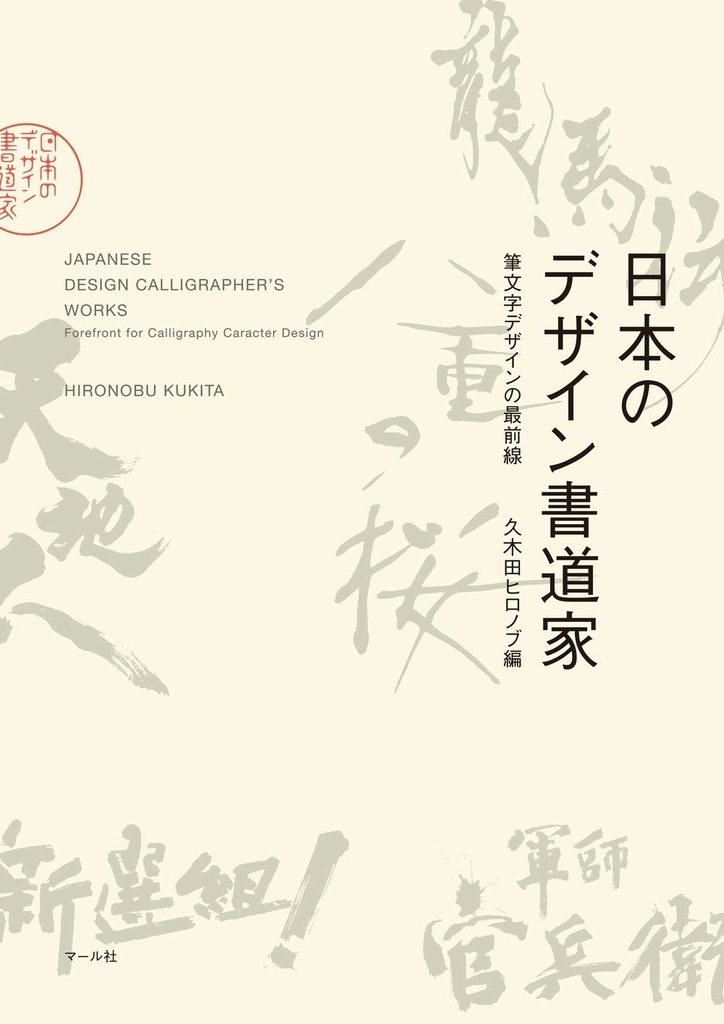
日本のデザイン書道家
29年にわたりデザイン書道作家として、テレビCMやポスター・書籍等の広告筆文字作品も手掛け、またデザイン書道の講師として指導に携わり、日本各地でワークショップを展開し多くのデザイン書道作家を輩出している久木田ヒロノブ氏編集による「日本のデザイン書道家」がマール社から2018年12月21日に発売された。
「日本のデザイン書道家」では第一線で活躍する書家や筆文字クリエイターの作品を作家ごとに掲載。更にデザインの考え方や制作の秘訣も紹介している。
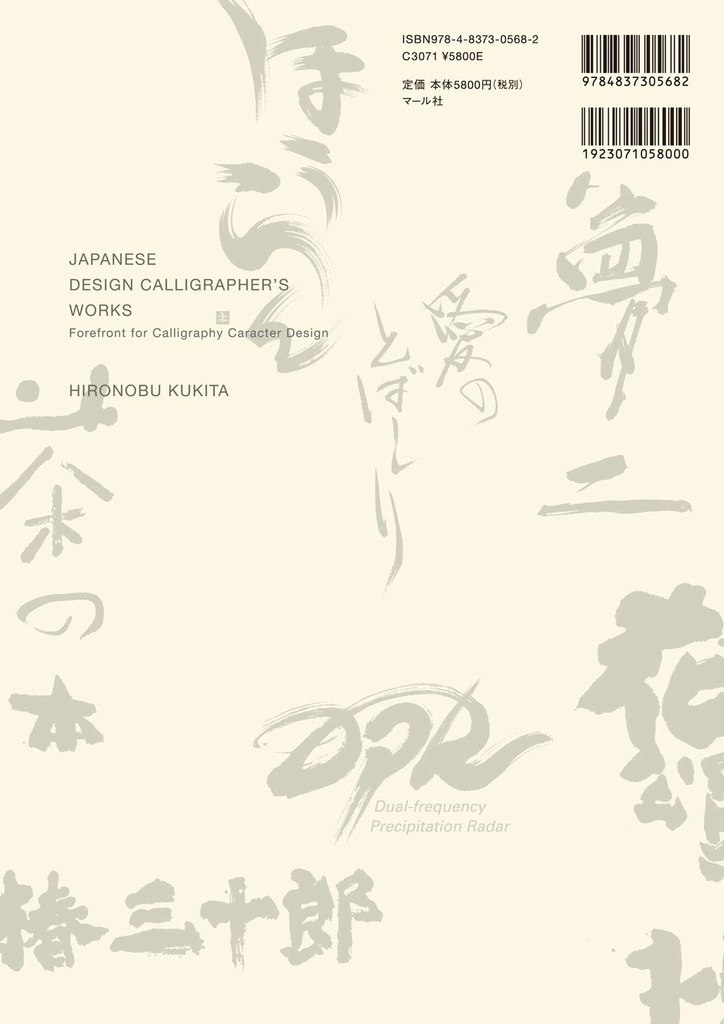
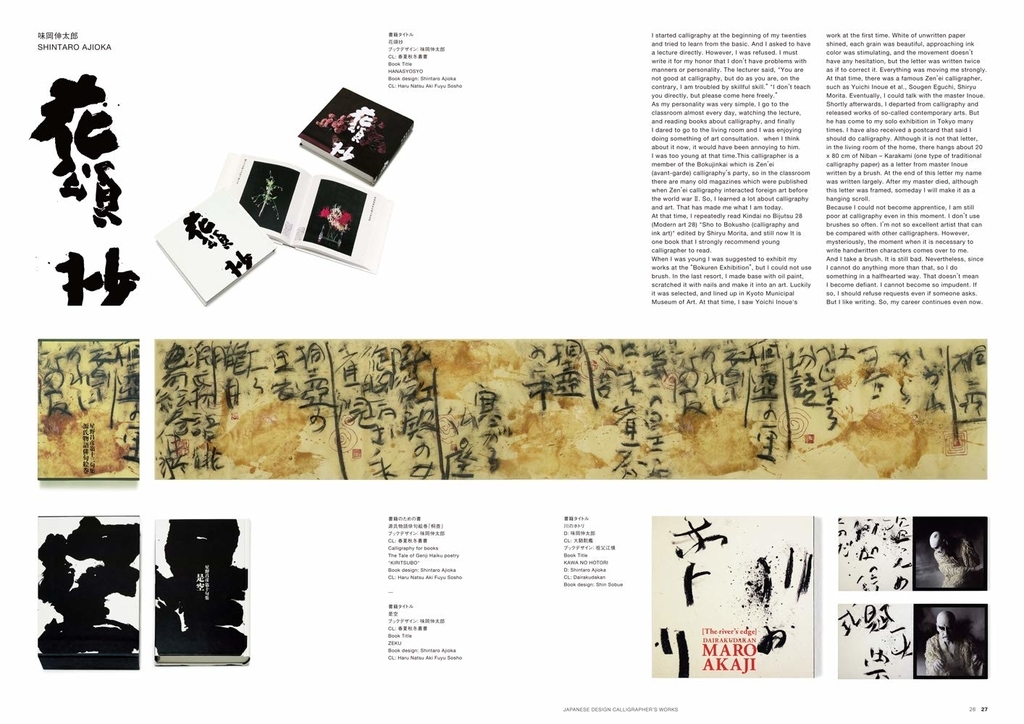
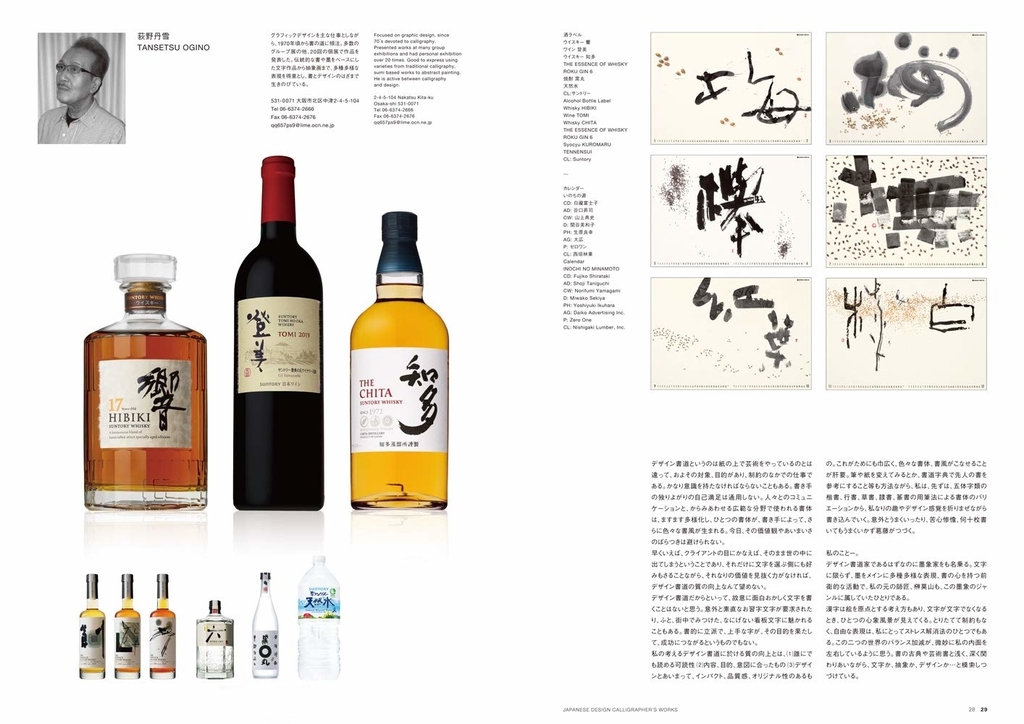
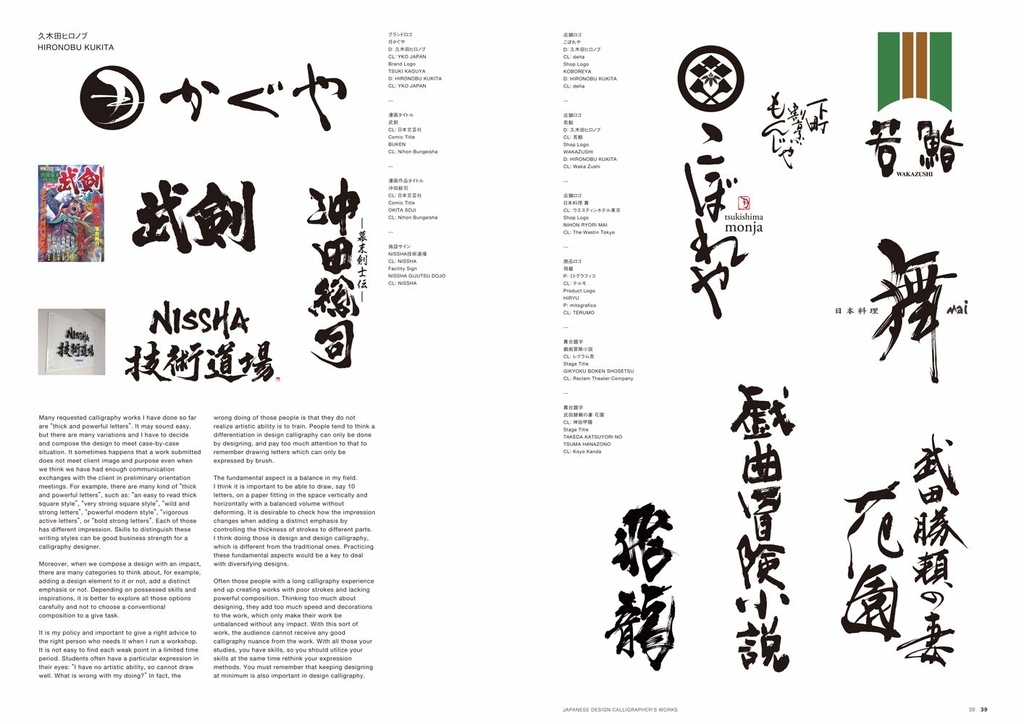
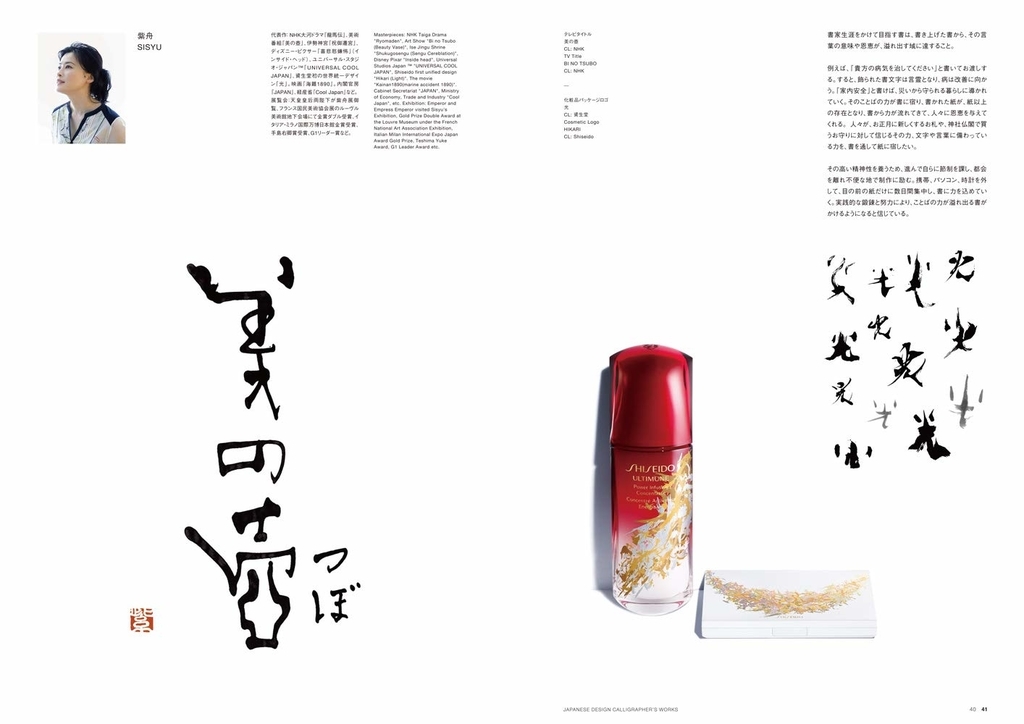
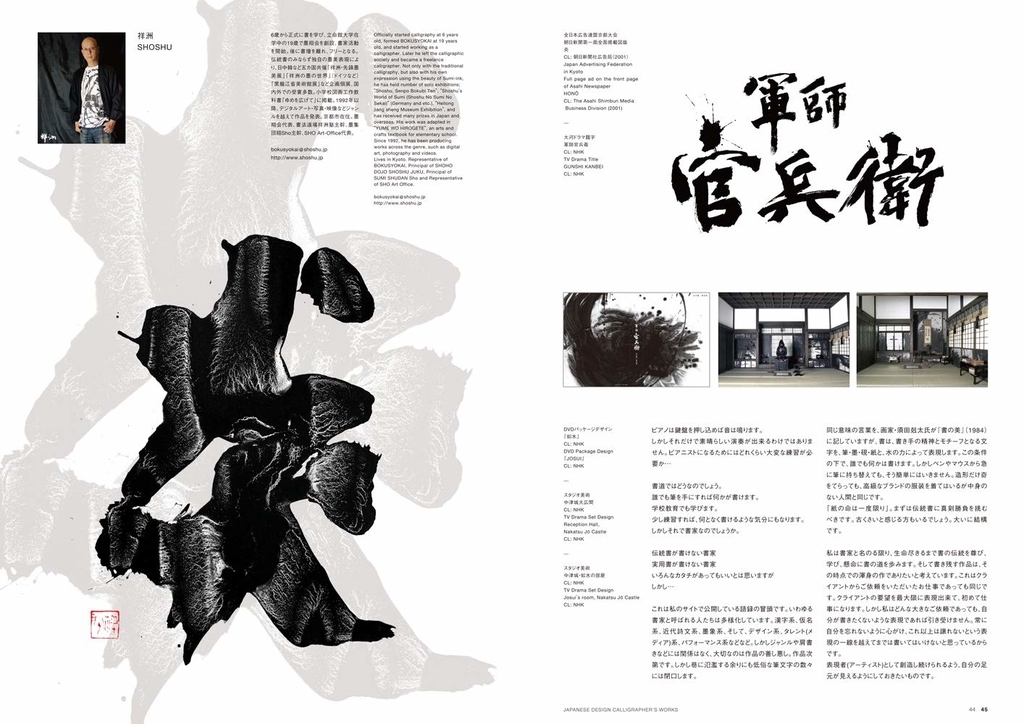
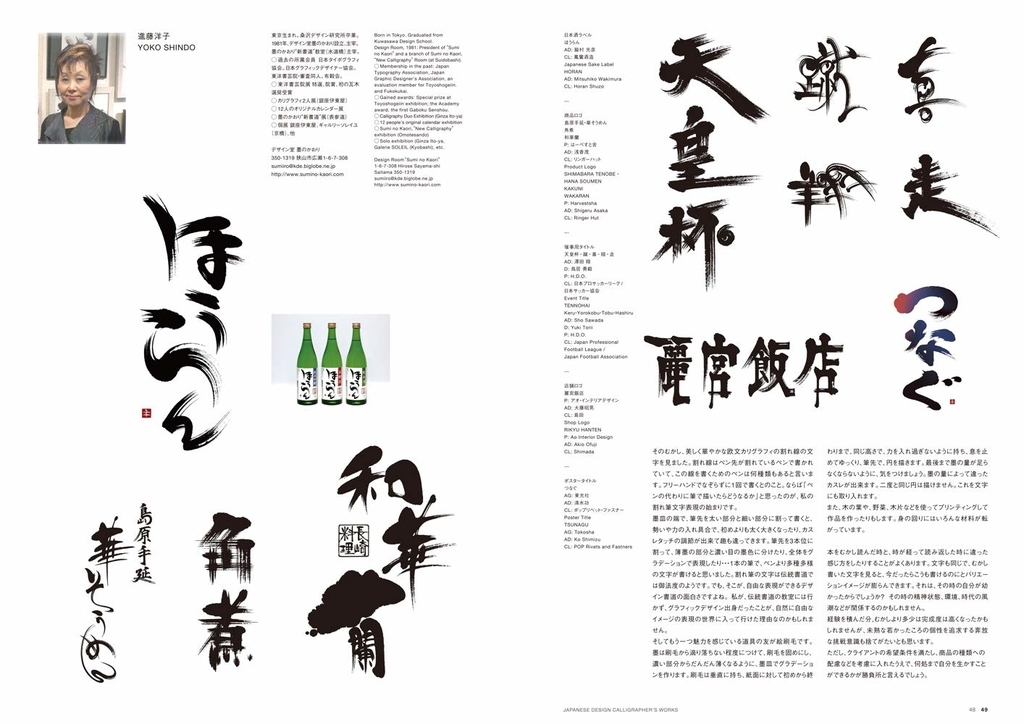
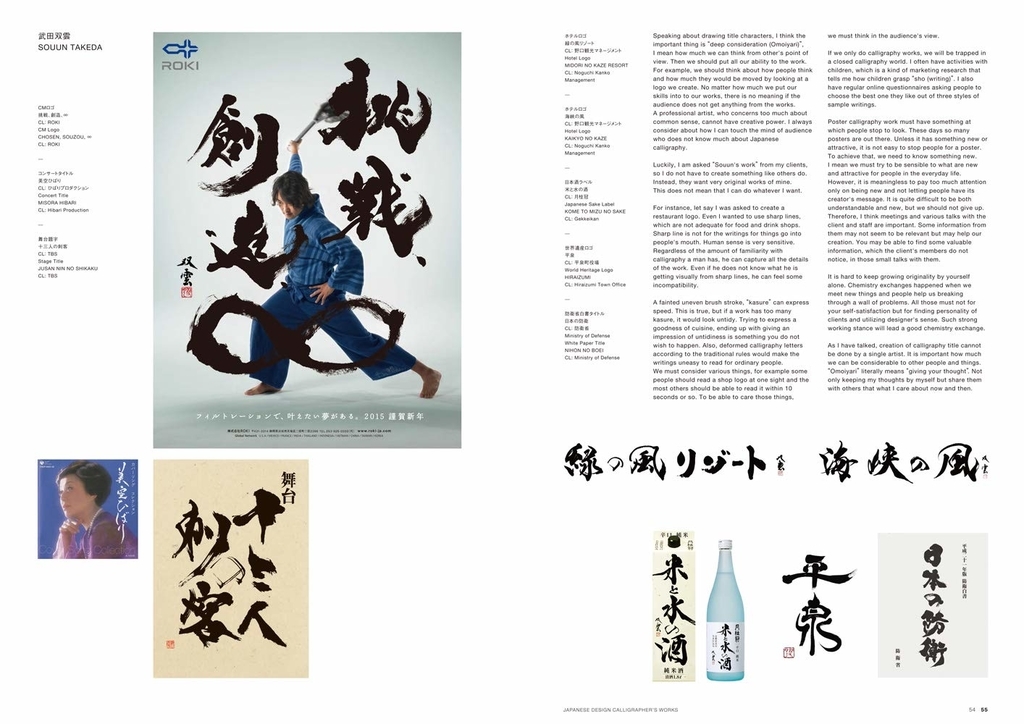
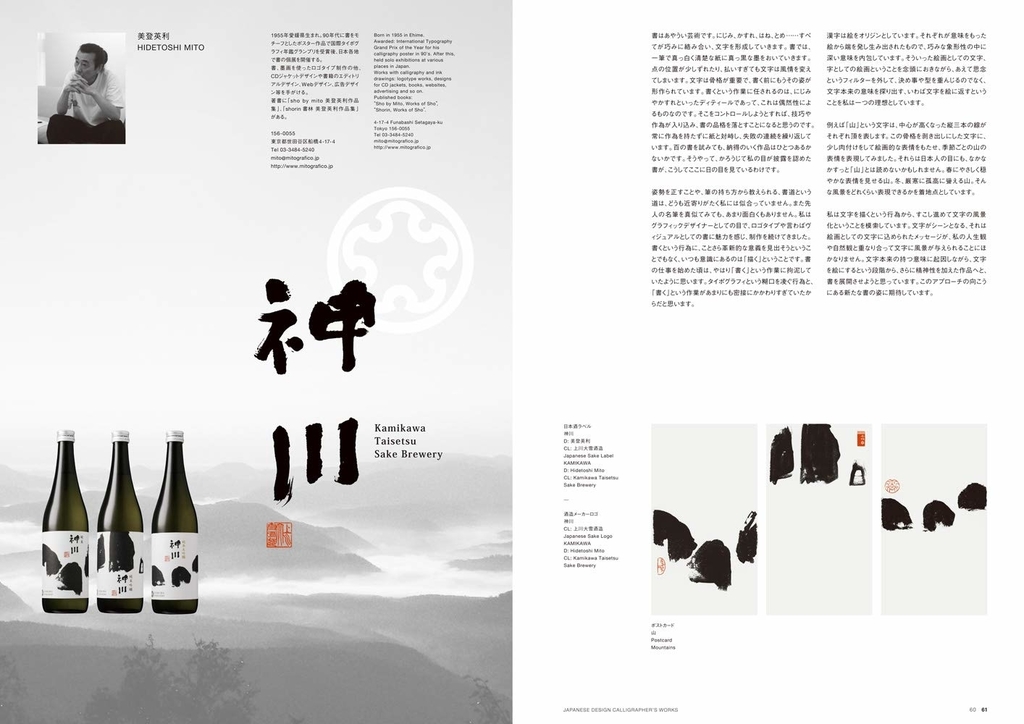
大河ドラマやTVCM、映画のタイトル文字、日本酒や和菓子などの商品名、お店の看板やメニュー、書籍や雑誌、チラシのような印刷物の見出しやタイトルなど、広告・デザイン業界では筆文字デザインの重要性が高まっています! 本書では第一線で活躍する書家・筆文字クリエイターの作品を作家ごとに一挙掲載! また、デザインの考え方や制作の秘訣も紹介。作家を知るための名鑑として、また書のお手本や参考として、デザイン書道に関わる人はもちろん、書家・筆文字クリエーターを目指す人も必携の一冊。 掲載作家は、荻野丹雪(新選組! )、赤松陽構造(八重の桜)、祥洲(軍師官兵衛)、紫舟(龍馬伝)、武田双雲(天地人)をはじめ140名以上。日英二カ国語表記。